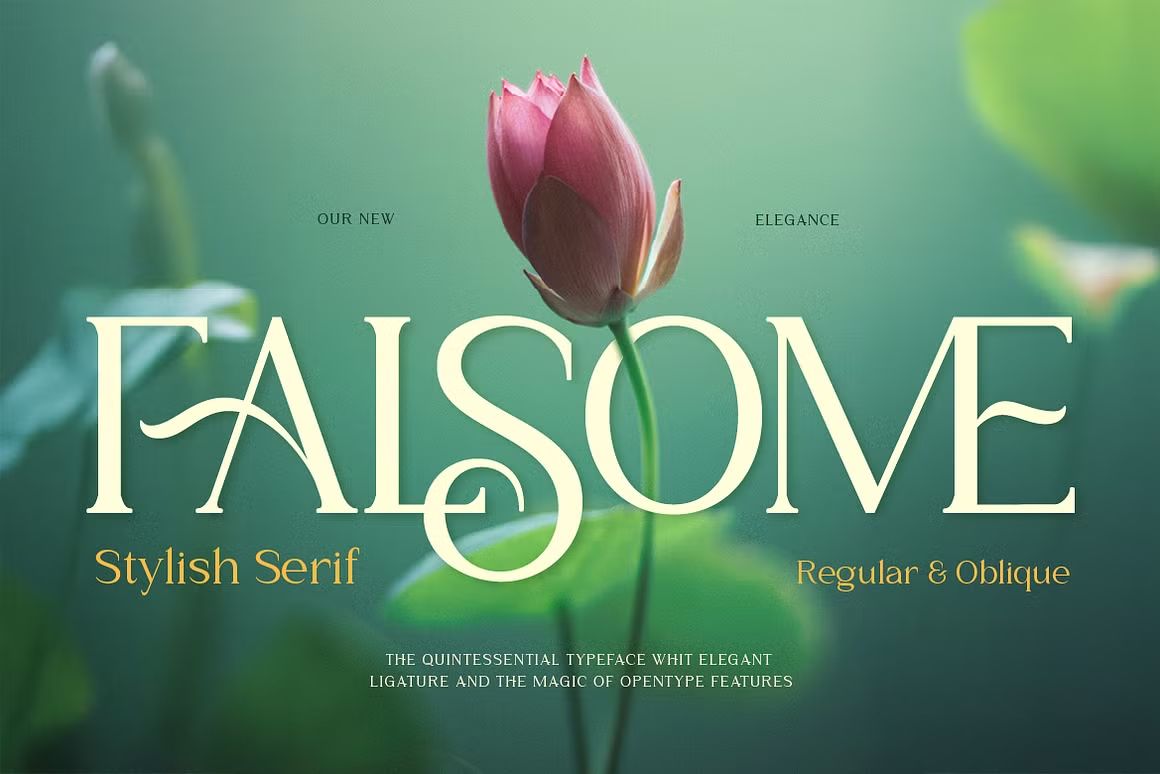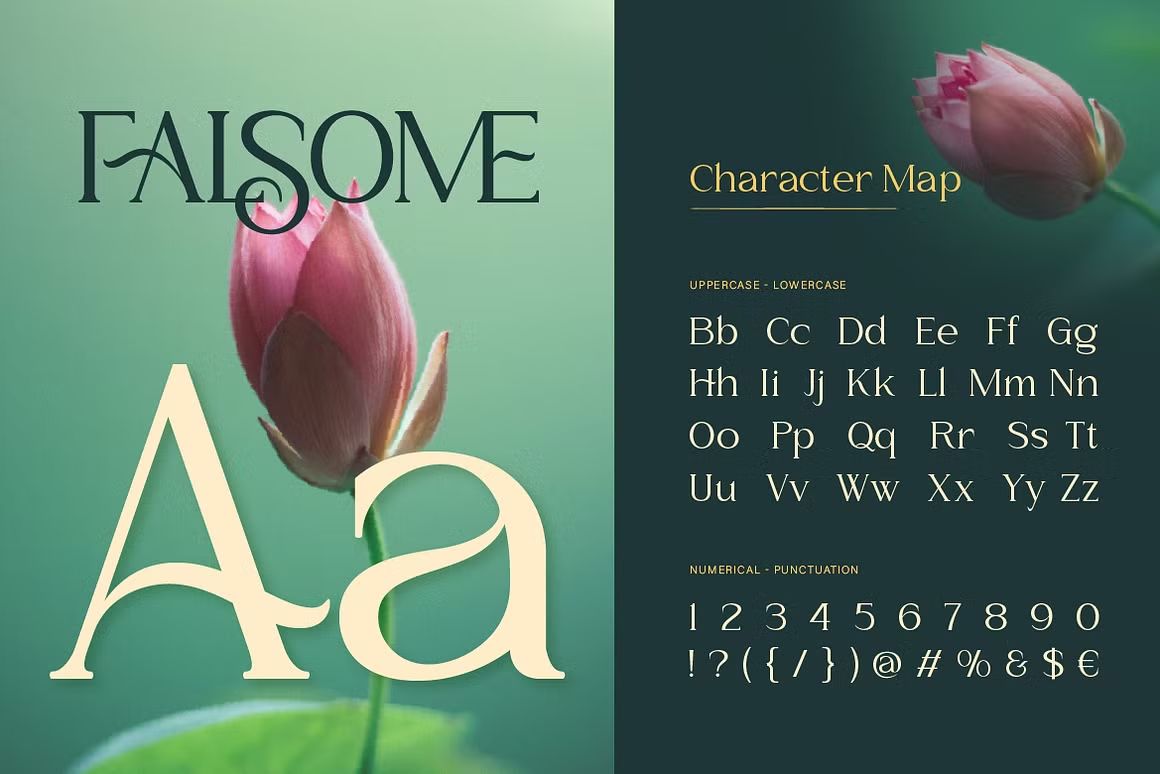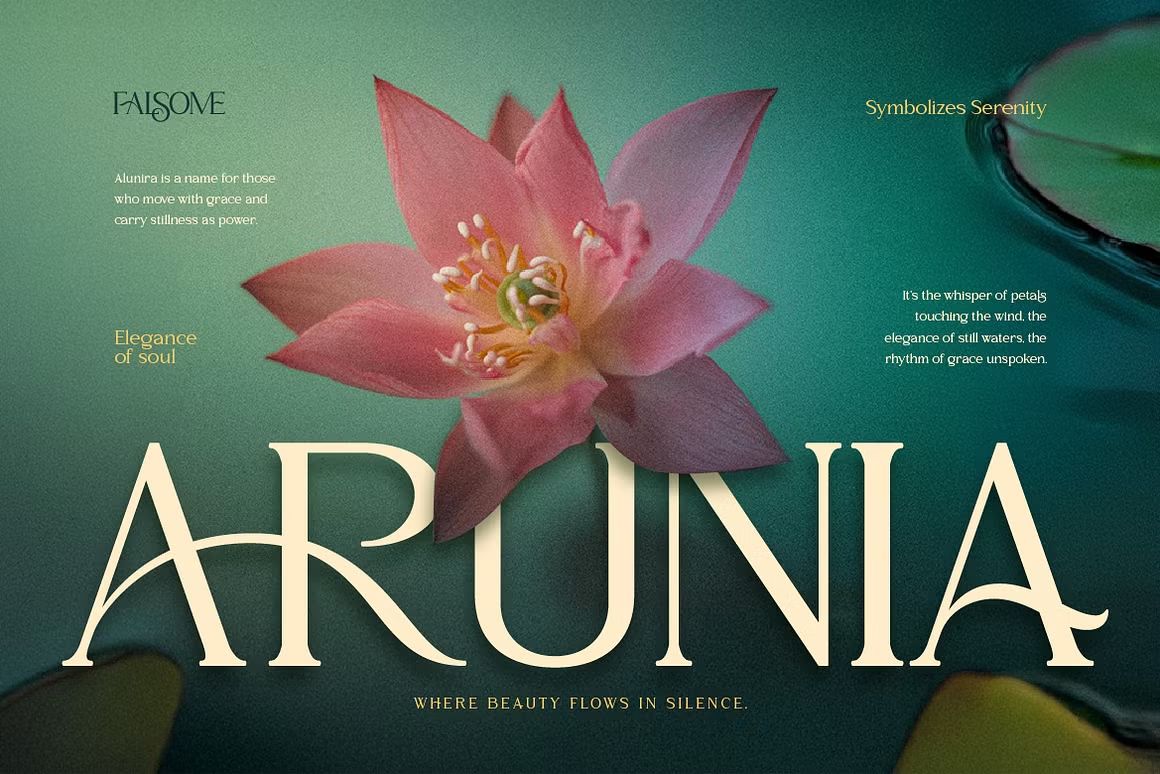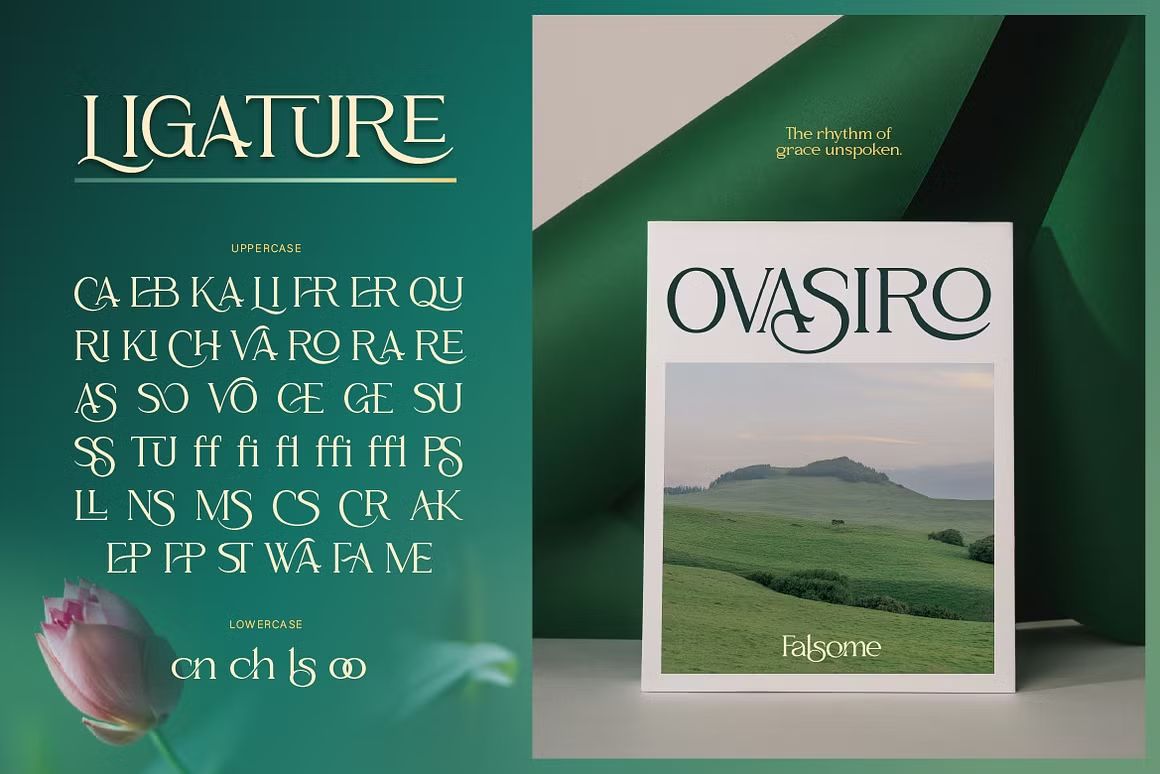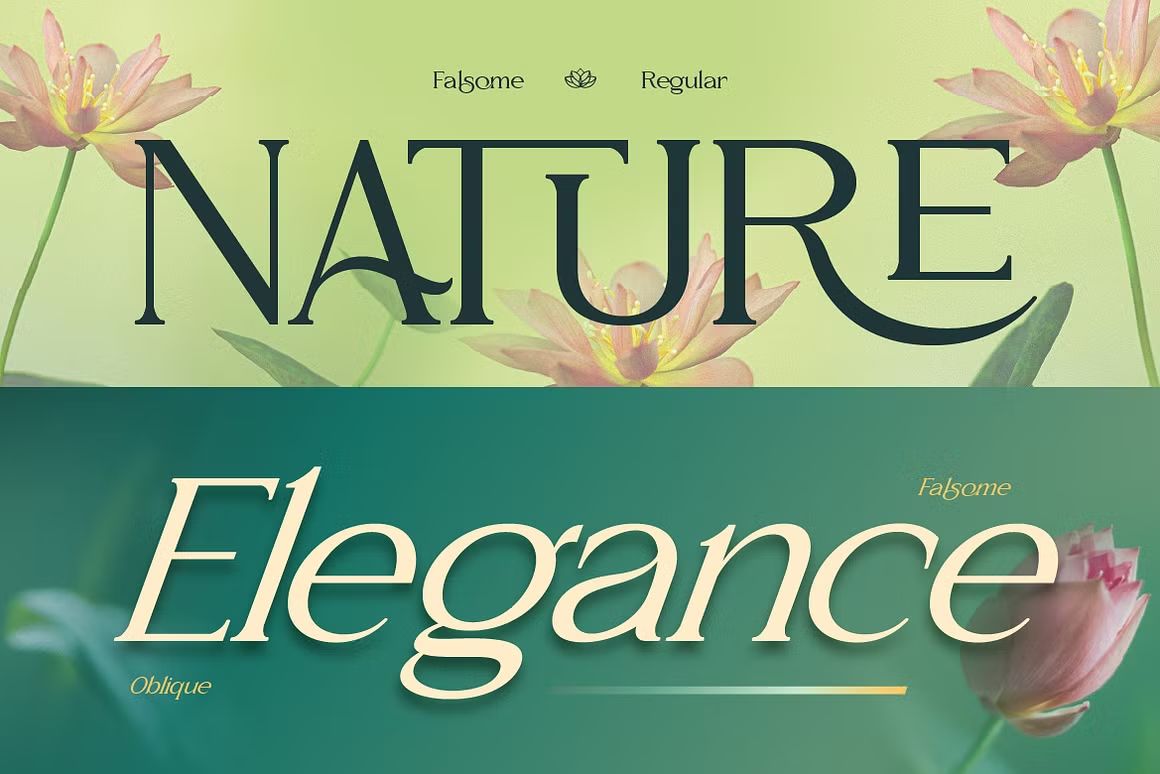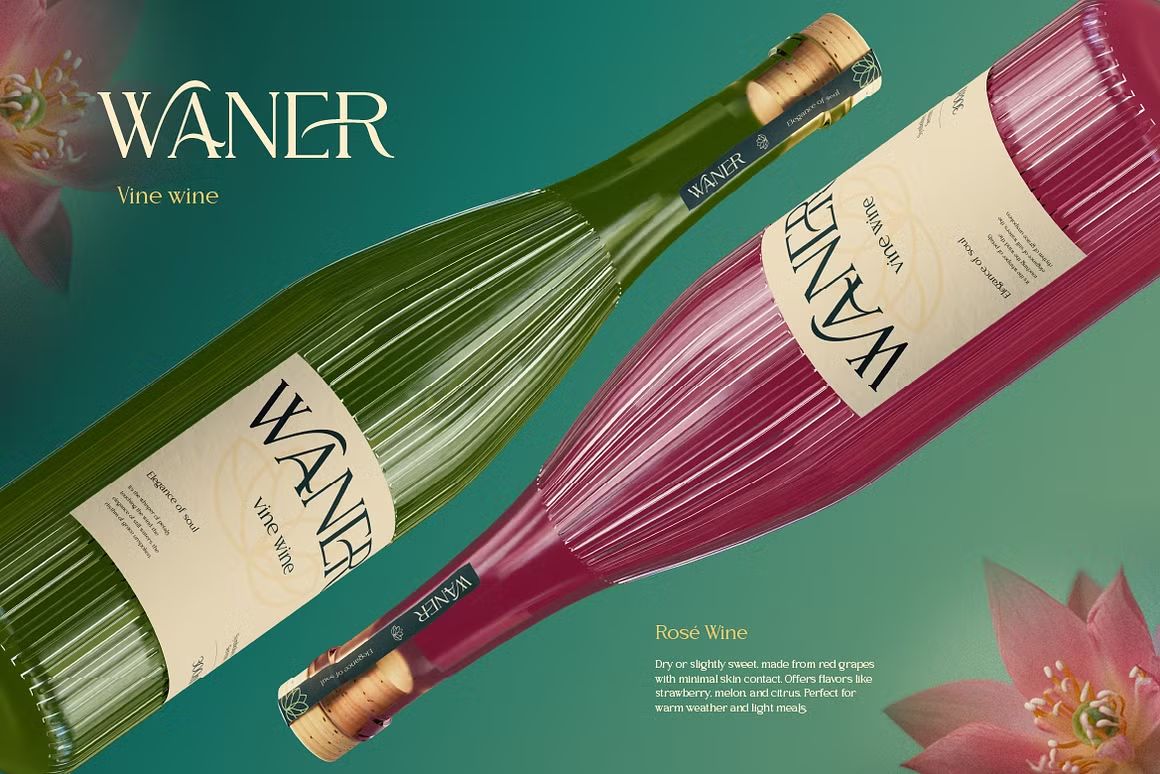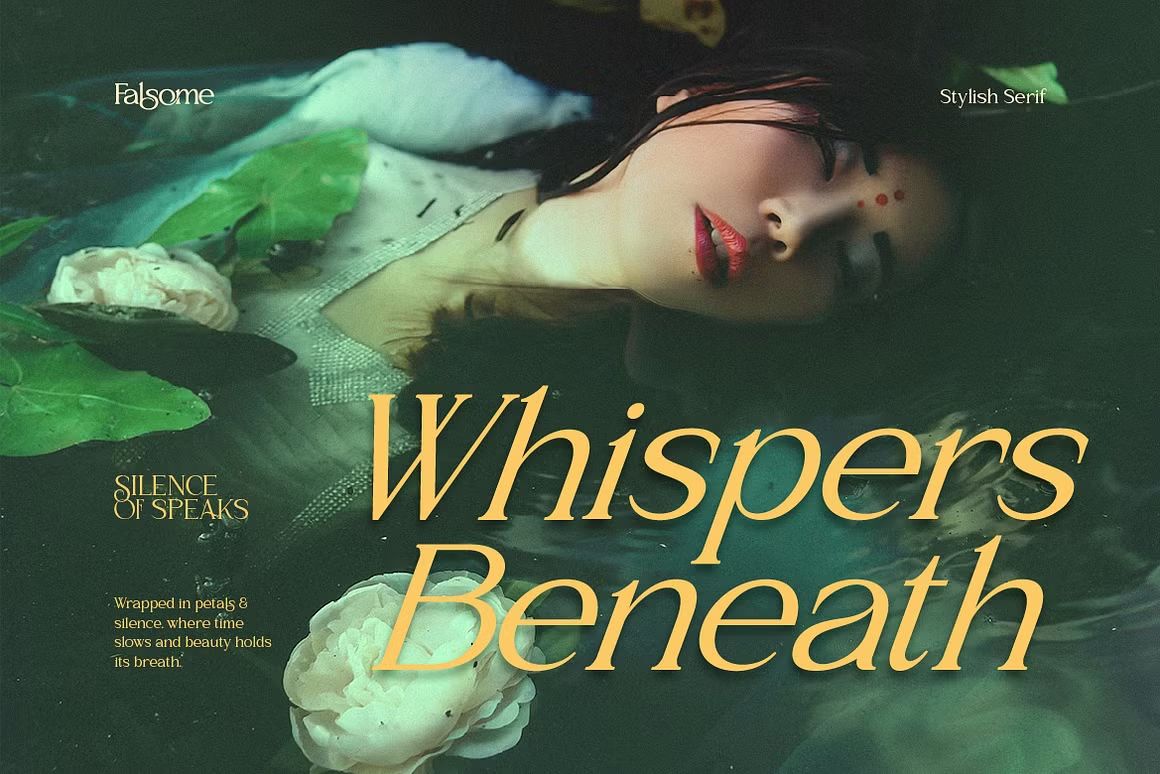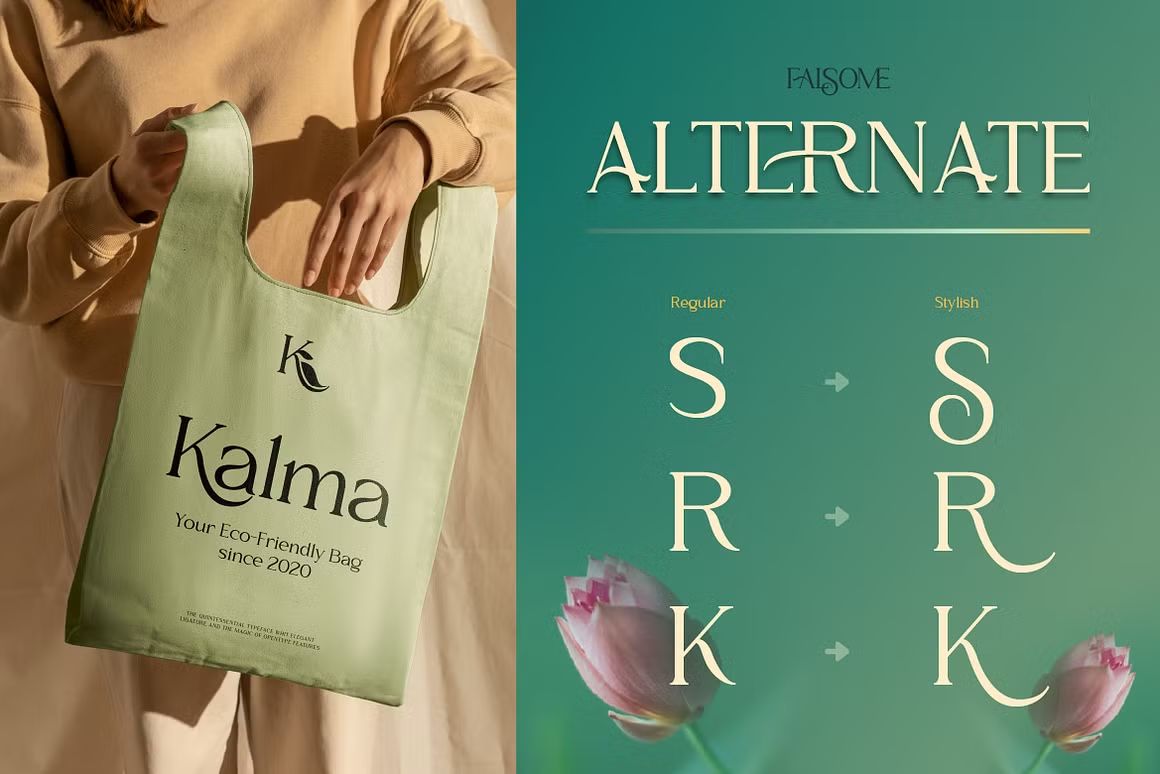
Falsome – Sans Serif Font
Falsome adalah font sans serif modern dan minimalis, ideal untuk branding dan desain profesional. Format OTF/TTF/WOFF, siap digunakan.
Falsome adalah font sans serif bergaya modern dengan desain bersih, kuat, dan minimalis. Didesain untuk tampilan yang elegan namun tegas, Falsome sangat cocok untuk branding, logo, desain editorial, kemasan, dan presentasi digital. Dengan garis geometris dan proporsi seimbang, font ini memberikan kesan profesional dan kontemporer di setiap proyek.
• Sans serif modern dengan gaya bersih dan solid
• Cocok untuk branding, desain digital, dan editorial
• Termasuk huruf kapital, kecil, angka, dan simbol